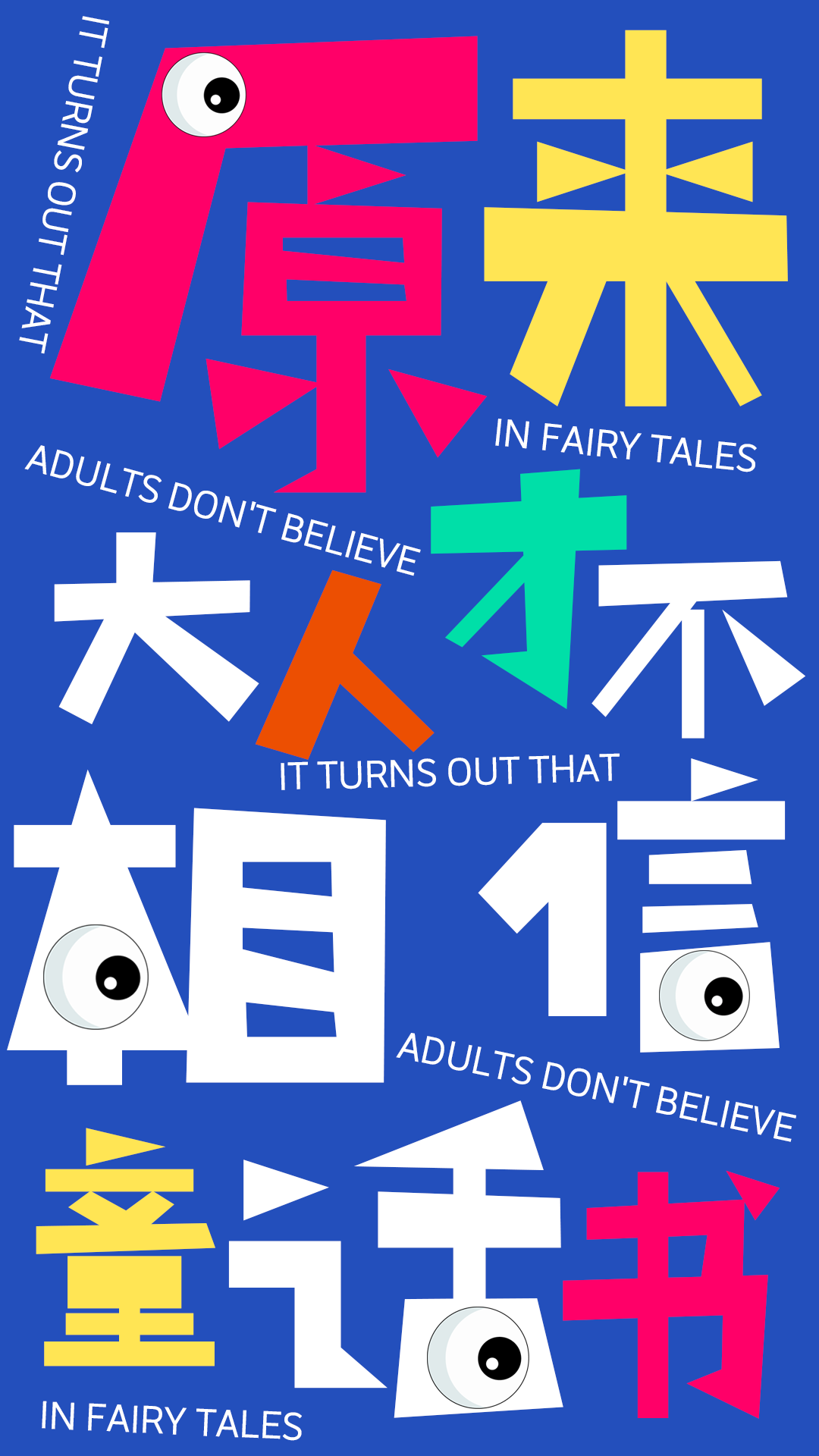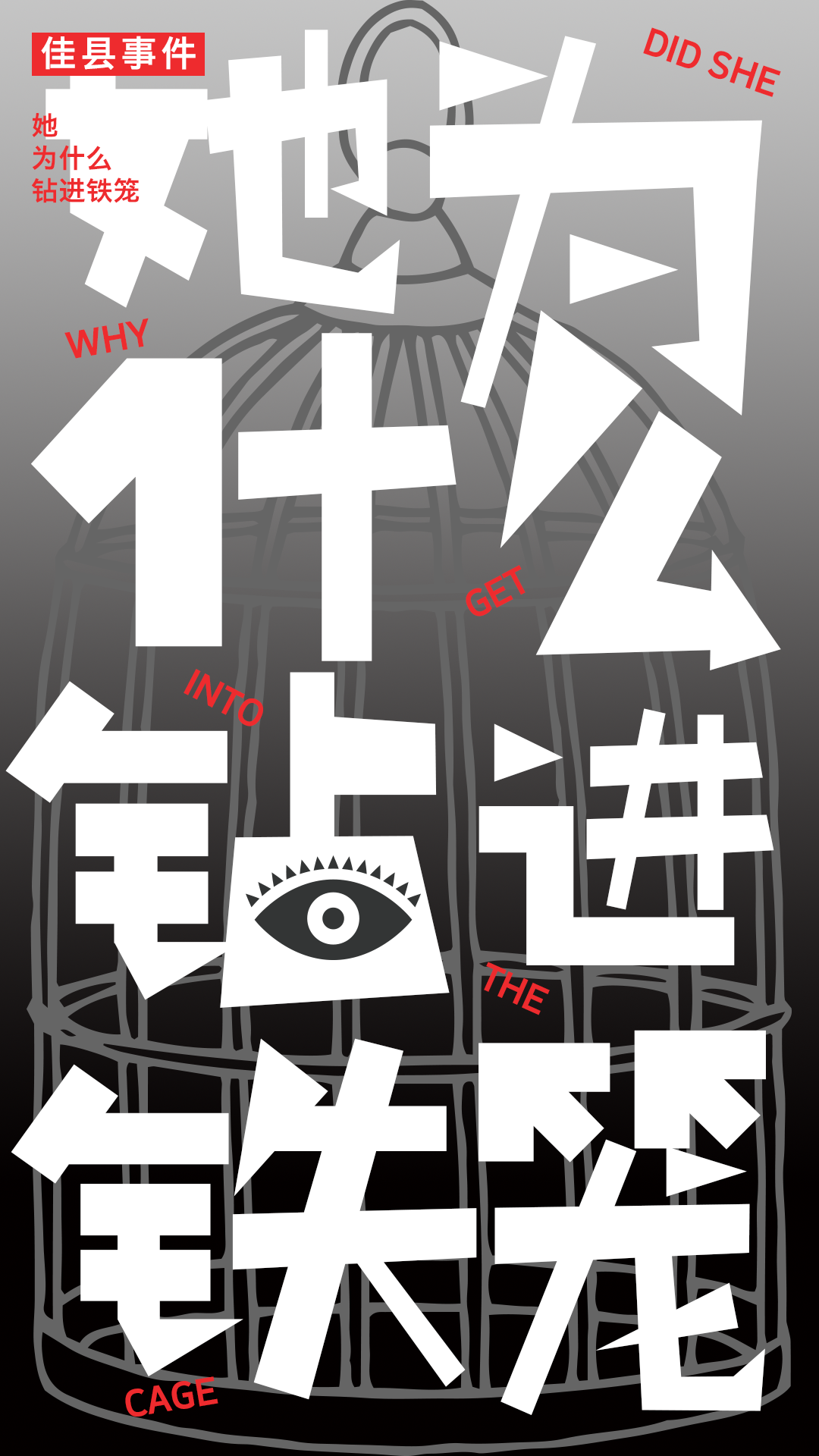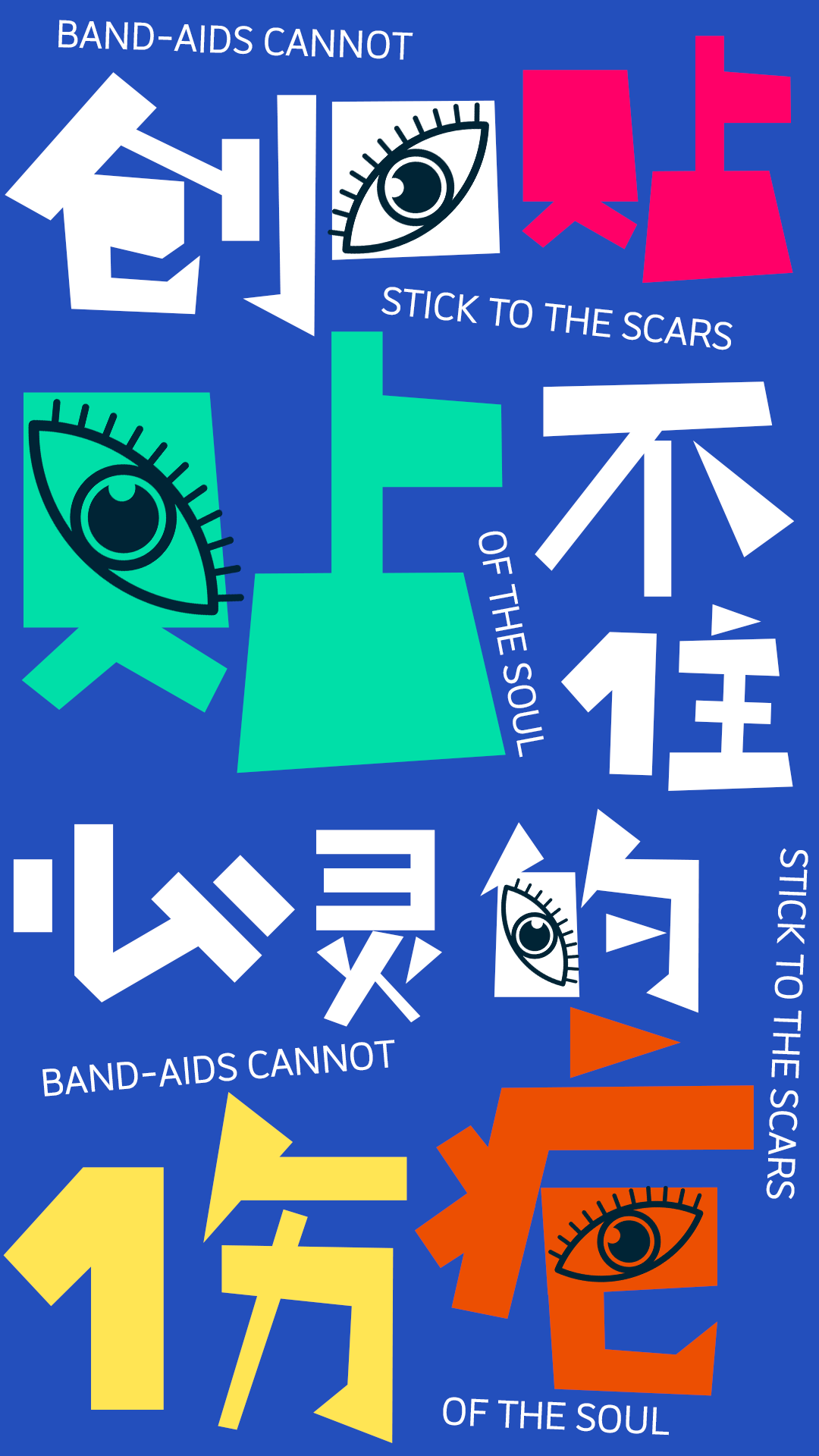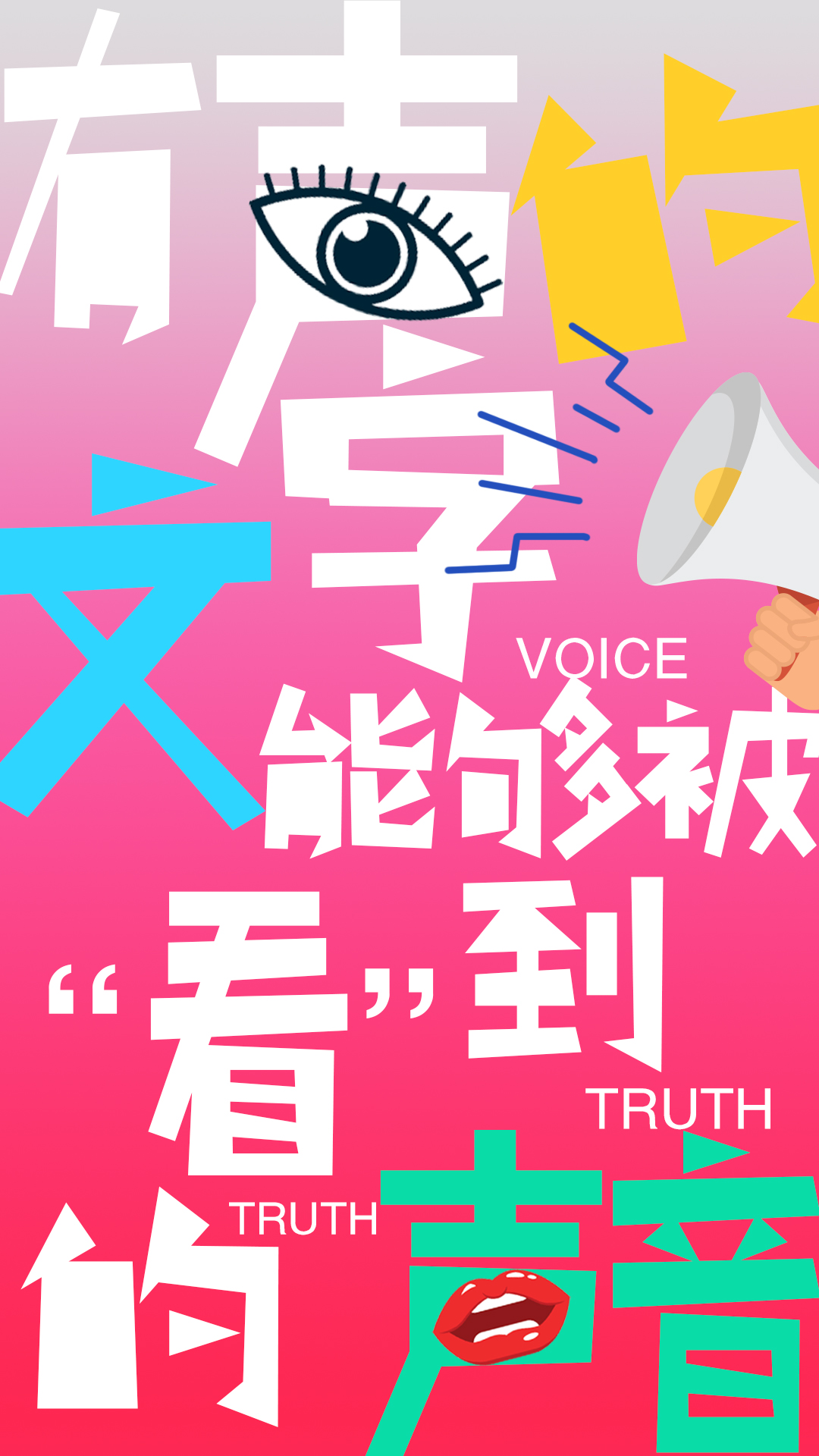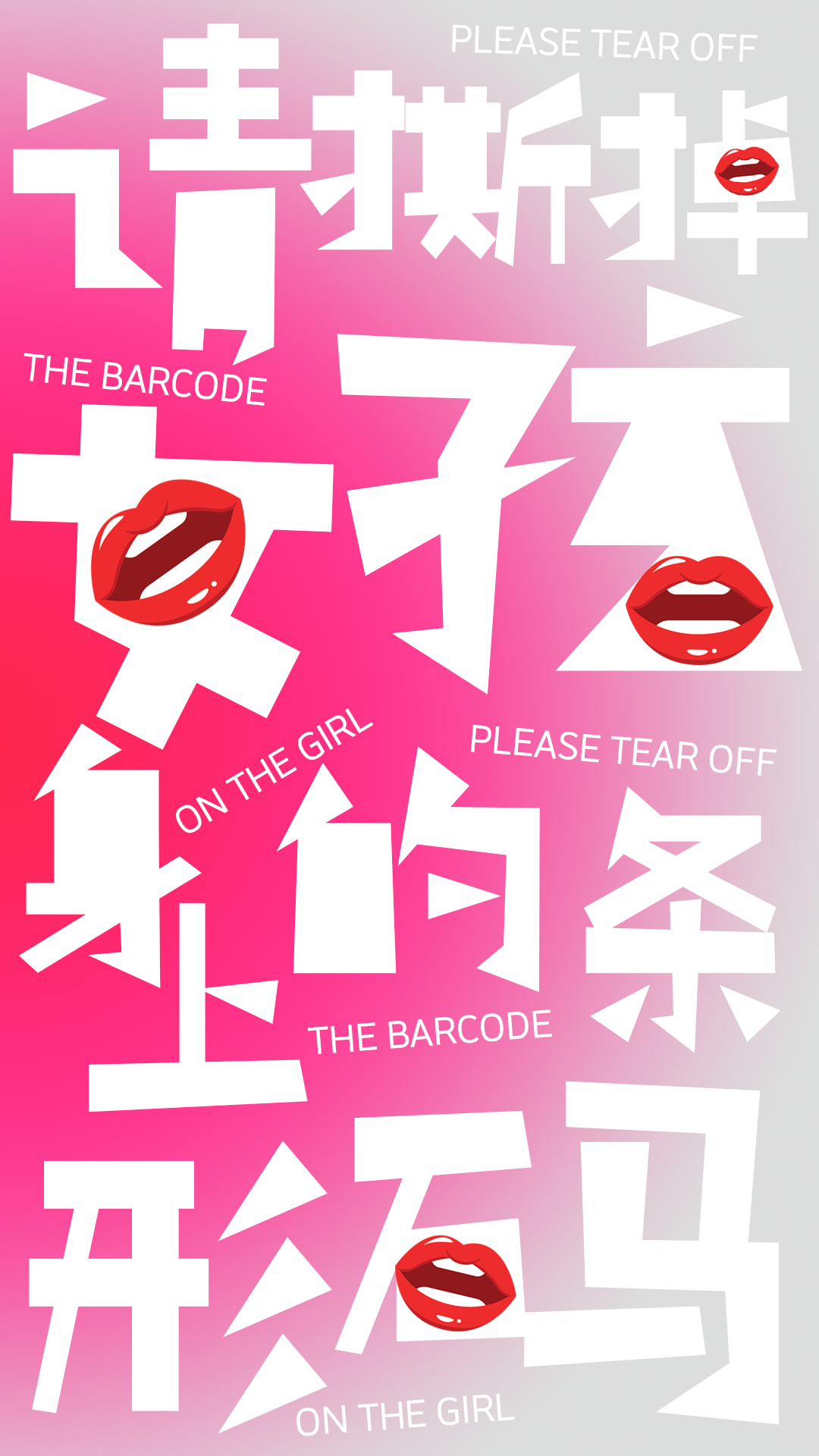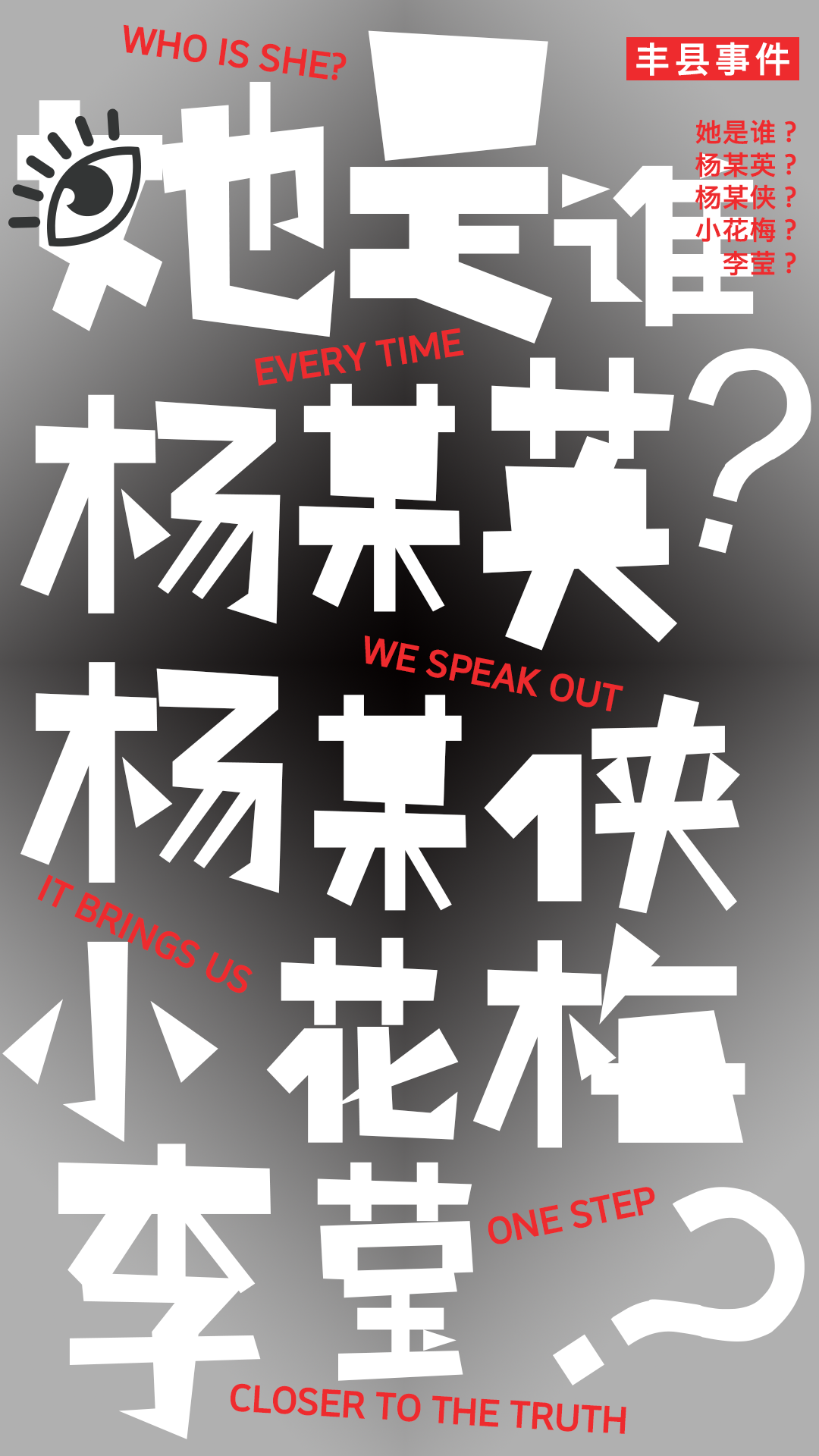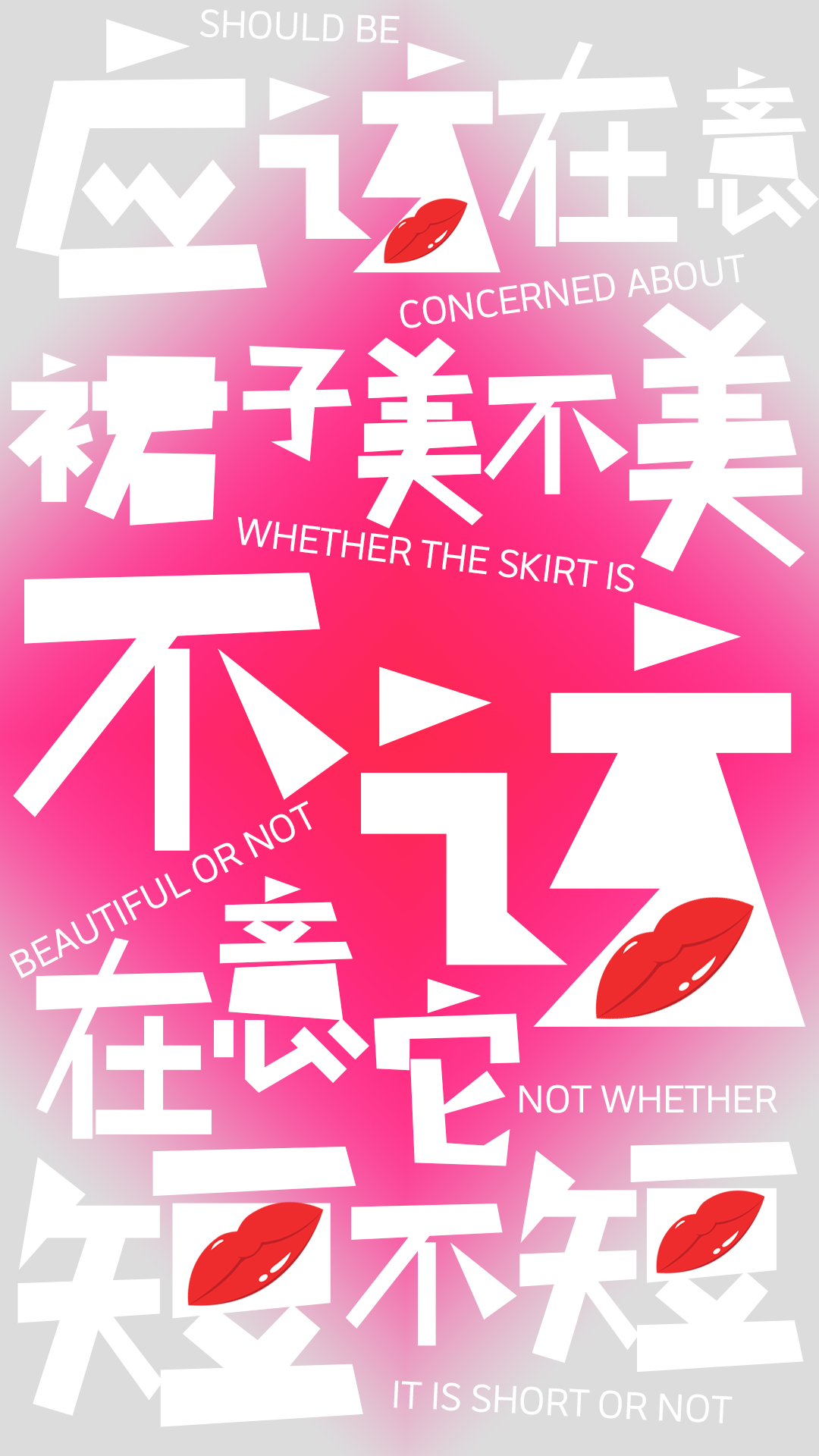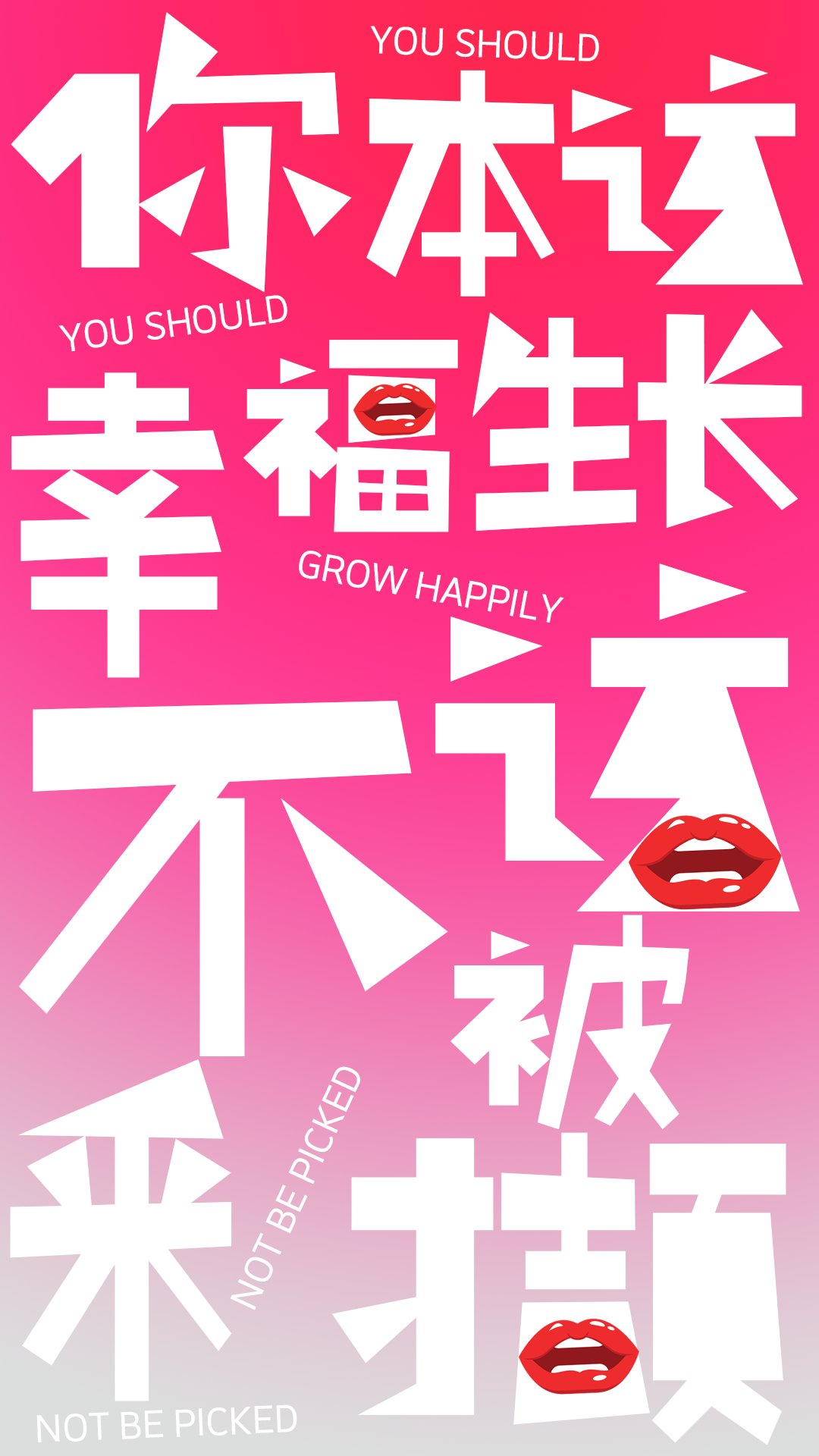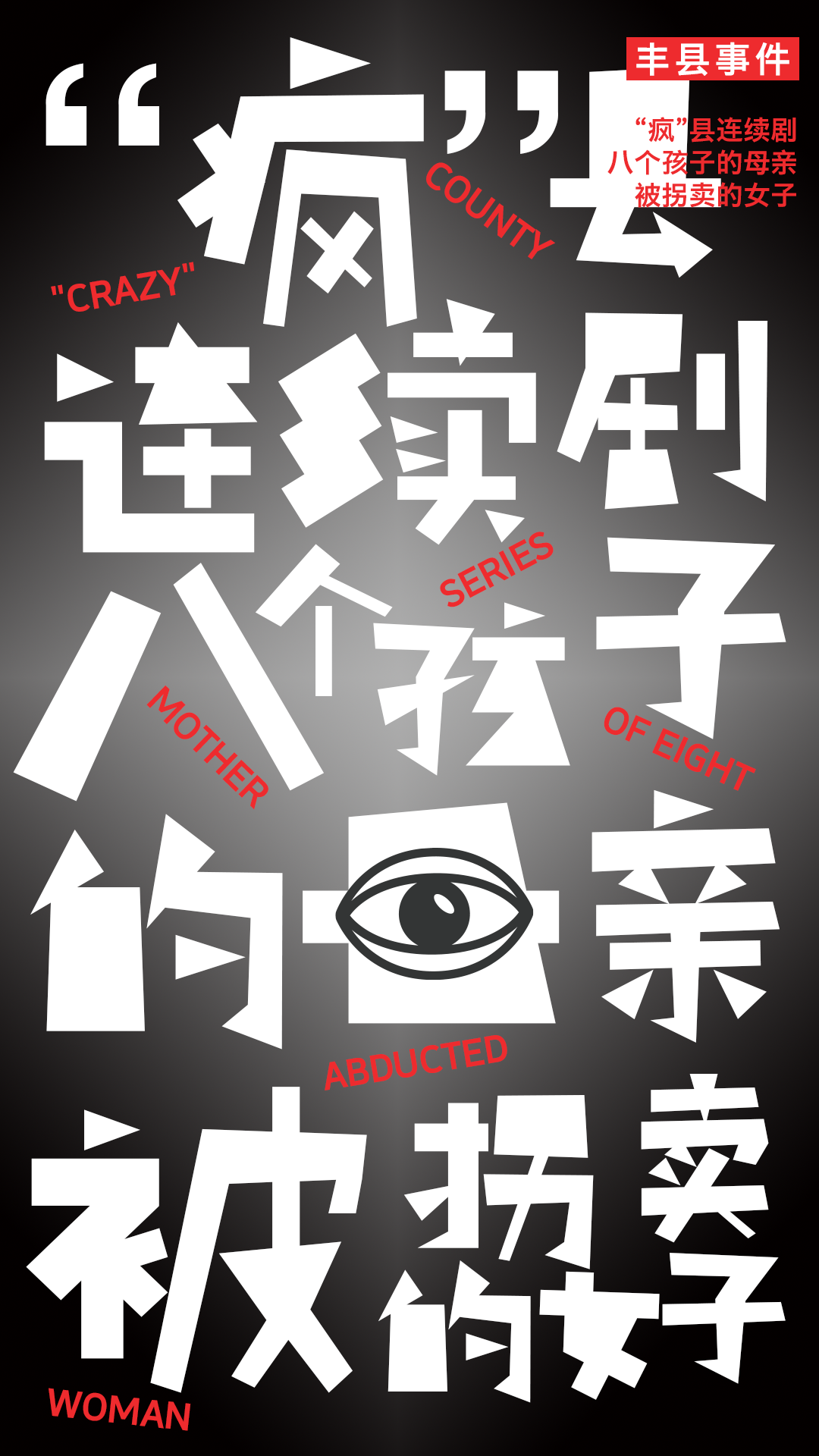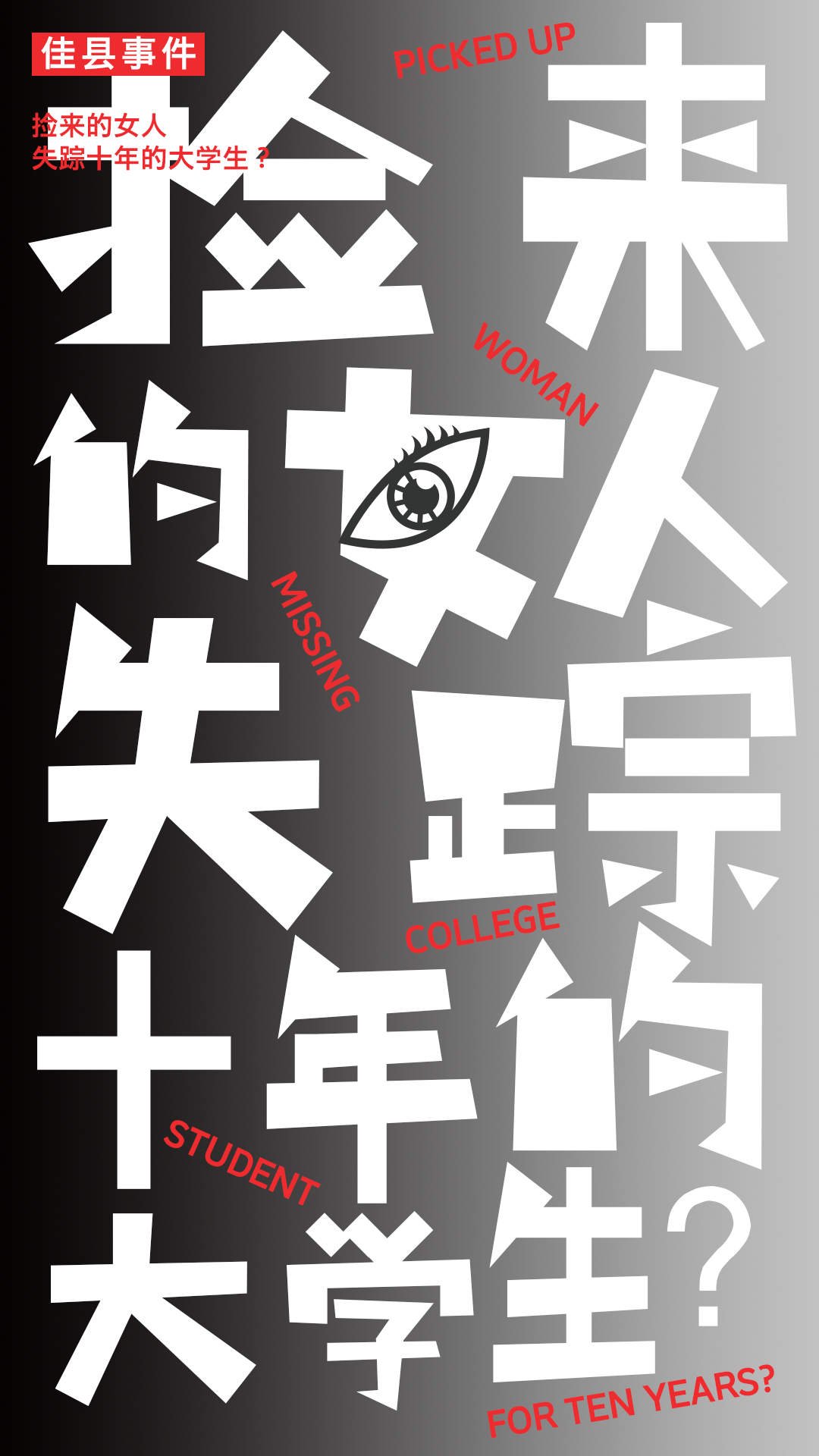
今日,公安部做出的这项重大决定,要回溯2022年初轰动全国的“徐州丰县八孩母亲”事件。大众难以想象,在经济实力雄厚的江苏地区,还隐藏着这样不为人知的悲惨现实。面对生活在冰冷房间中的“铁链女”,人们在难过和愤怒的同时,开始追问事件真相。
于是网友纷纷自发贴子、转载文章,丰县事件一下子冲到热搜榜一,成为爆炸新闻。这一次,在罪恶面前,热心网友不再“吃瓜”,而是直言疑虑、问题,每一次发声,都让我们离真相更近一步。经过五次官方通报,沸沸扬扬一个多月,最终丰县事件水落石出,真相大白,涉案人员也依法得到严惩。
◎网络流传视频中,八孩母亲在寒冷的冬天衣衫单薄地被关在小黑屋里,桌上只有一碗凉粥,她被铁链锁住,精神状态异常。
◎“她”的身份成谜,最开始大家猜测她是李莹,经过证实排除后,官方确认“小花梅“、杨某侠、杨某英实际系同一人,就是视频中的女子。
◎随着调查深入,得知女子经历了人贩子的三次倒卖,最终来到丰县,被董某民父亲买下,十余年间为其儿子生育了8个孩子。目前女子得到医治救助,相关涉案人员被绳之以法。
然而在丰县事件告一段落之时,“陕西铁笼女”又被曝出。网友披露,陕西佳县一名男子在社交媒体上,以直播“铁笼女”来炒作赚钱。
◎有爱心人士反映,铁笼是男子为防止女子逃跑安装在三轮车后的,上边还有一把大锁。女子看到有人来后受惊钻进铁笼,这就是“铁笼女”的由来。
◎直播男子称女子是他“捡来的”,大众猜测她很可能是十年前失踪的女大学生“王国红”。
◎据网友称,这名男子在平台拥有十万粉丝,在直播时自曝自己把亲生女儿以三万元卖给邻村。
吸取丰县事件教训,这次官方立即作出反应,成立调查组,目前大众正在等待事件真相与调查结果。
丰县事件、佳县事件绝不是孤立事件,它反映出来的是这片土地的历史与社会问题——拐卖妇女儿童的残酷真相。不难看出,这类社会事件的受害者,都是妇女儿童等弱势群体,也许被铁链锁住的、关在铁笼里的,不止一个。所以丰县事件远没有结束,我们不能终止发声!
值得欣慰的是,我们的发声已有回响:公安部已部署全国公安机关开展打击拐卖妇女儿童犯罪专项行动。为此,锐字潮牌字库推出一款快闪定向免费公益字体——锐字真言刺破公益免费,希望大家能够持续关注相关事件,揭开真相,为弱势群体发声。
设计理念——
有声的文字:用字体讲真言,刺破隐藏的真相。
本次发布的锐字真言刺破公益免费,用文字说真话,刺破隐藏的真相,表达对社会不公正事件的批评与反思,为社会公平正义而呐喊。为助力公益事业,该字体提供在公益组织、公益活动、公益报道中免费使用,目前已上线并开放下载。
公益字体——
反传统设计:黑块覆盖与锋利尖角,象征反对虚假与伤害。
该字体一改传统意义上的笔画和结构,是由图形拼接而成,仿佛在将一些事实片段重新拼凑起来,还原出最本质的真相。
部分封闭笔画用纯黑色填充,在字体中形成一个完整的黑色不规则块状图形,象征着一些被掩盖的、难以言喻的事实真相。想要从反面来表达:面对社会问题,我们要做的不应该是去遮掩,而是揭开事实真相,鼓励更多人站出来用“真言”发声。
除此之外,另一直观特点是,将部分点画、钩画、折笔处等设计为锐利的尖角形态,如刀锋一般直直刺出,用一种抵御外界伤害的姿态,传达希望保护弱势群体的关怀。同时也意味着直言真话,以及勇敢、坚强、有锋芒,象征着正义和正直永远不会被磨平棱角。
公益海报——
直面现实:最重要的并非刺破真相本身,而是我们如何去做。
尽管在丰县事件、佳县事件中,我们都不是当局者,但我们每一个人都不能置身事外。因为Ta可能是我们的母亲、孩子、朋友,是与我们生活在同一方水土的“人”。
于是我们设计了系列公益海报,来为妇女儿童发声,呼吁大家为保护社会弱势群体奉献微薄之力。希望今后的社会环境,能够让女性免遭非议与苦难,让孩童健康快乐地成长。
关爱妇女系列海报👇
关爱儿童系列海报👇
字体设计师——
用字体对社会现象进行思索与探讨。
字体设计师:谢宇,平面设计师,本科毕业于仲恺农业工程学院,研究生就读于广州美术学院,REEJI锐字潮牌字库签约设计师。
设计指导:吴绮虹,设计师、高校教师、中国出版协会书籍设计艺术工作委员会委员。
锐字真言刺破公益免费,字库设计来源于作品《标签×地域》,曾获得多个国际奖项:GDC17学生组出版物最佳奖、提名奖、评审奖;2017白金创意学生平面设计大赛全场大奖、评审奖;第九届全国书籍设计艺术展银奖;2018靳埭强设计奖专业组优秀奖;2019Design 360 Award年度100;入选2019东京字体指导俱乐部tokyo TDC。
《标签×地域》简介:人们对某个地区及人的偏见,形成于对其的刻板印象;地域歧视充斥在当代社会中,由刻板印象提取木刻版画为概念,将其特有的视觉语言融入字形设计,进行刻板字体的探究;被省略被遮挡的笔画细节,如同刻板印象使人们无法看到本质而产生偏见。“刻板”的字体结合尖锐的标签语言进行编排,呈现出的画面令人产生不适感,从而引发人们对歧视偏见的重新思考。
文章标题:锐字真言刺破体公益免费上线开放下载!讲真言,刺破真相